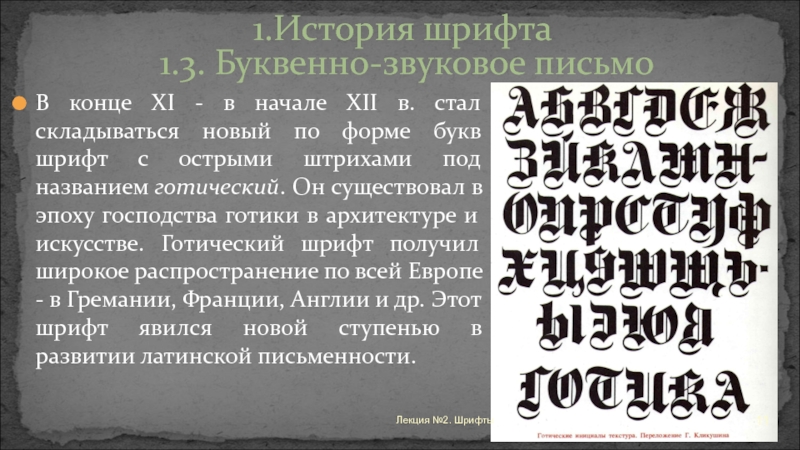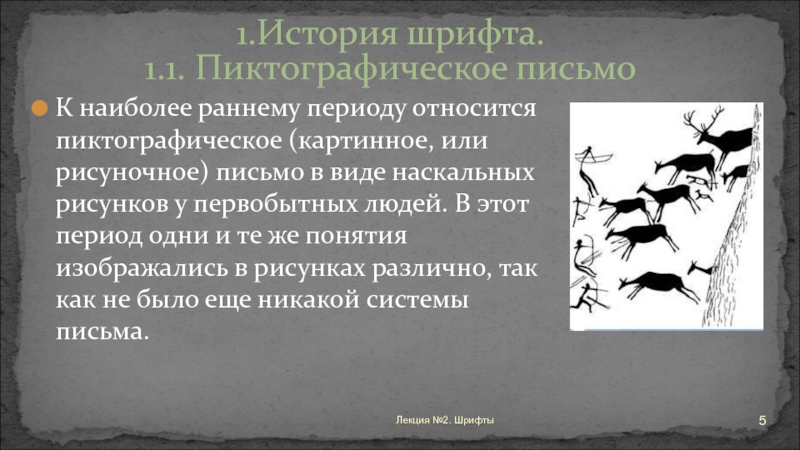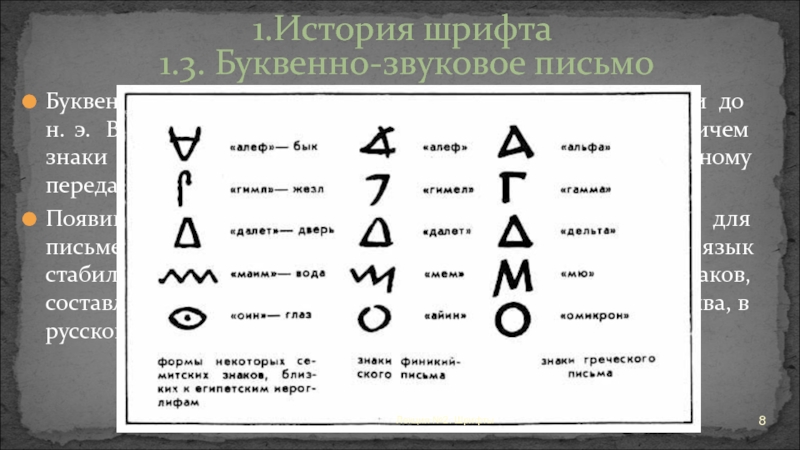
ОФОРМЛЕНИЕ. ШРИФТЫ
Слово "шрифт" в переводе с немецкого означает - начертание букв, письмо. Шрифт - это алфавит с четким определением закономерности построения изображений букв, цифр и других письменных знаков, объединенный в единый стиль.1.
Слайд 1Одно из величайших и важных достижений человечества - это общение
при помощи письменных знаков: шрифта.
ОФОРМЛЕНИЕ. ШРИФТЫ
Одно из величайших и важных достижений человечества - это общение при помощи письменных знаков: шрифта.ОФОРМЛЕНИЕ. ШРИФТЫ
Слайд 2Слово "шрифт" в переводе с немецкого означает - начертание букв,
письмо.
Шрифт - это алфавит с четким определением закономерности построения
изображений букв, цифр и других письменных знаков, объединенный в единый стиль.
1. История шрифта
Слово
Слайд 3Как правило, шрифт разрабатывается с учетом предполагаемой области его использования
- это книжная или журнальная продукция, научная или художественная литература,
детские или учебные издания.
Иногда шрифты, разрабатываются для узкого внутрифирменного применения, становятся всеобщим культурным достоянием. Например, шрифт Times в свое время был разработан для текстового набора газеты "The Times", шрифт Frutiger разрабатывался для визуальных коммуникаций парижского аэропорта
1. История шрифта
Как правило, шрифт разрабатывается с учетом предполагаемой области его использования - это книжная или журнальная продукция, научная
Слайд 4Рисунок знаков прошел длительный и сложный путь, прежде чем он
стал алфавитом. Всего четыре вида письма удалось разгадать:
пиктографическое
идеографическое
слоговое
буквенно-звуковое
1.История шрифта
Рисунок знаков прошел длительный и сложный путь, прежде чем он стал алфавитом. Всего четыре вида письма удалось
Слайд 5К наиболее раннему периоду относится пиктографическое (картинное, или рисуночное) письмо
в виде наскальных рисунков у первобытных людей. В этот период
одни и те же понятия изображались в рисунках различно, так как не было еще никакой системы письма.
1.История шрифта. 1.1. Пиктографическое письмо
К наиболее раннему периоду относится пиктографическое (картинное, или рисуночное) письмо в виде наскальных рисунков у первобытных людей.
Слайд 6В Китае и в Египте на смену пиктографическому письму пришло
идеографическое,  т. е.  письмо при помощи идеограмм, а не букв.
Одним письменным знаком обозначалось целое слово.
Это уже была система графических форм, поскольку последовательность знаков соответствовала порядку слов в речи. Предметы изображались либо символическими знаками (солнце, луна), либо графическими изображениями: птица, зверь и т. д.
1.История шрифта. 1.1. Пиктографическое письмо
В Китае и в Египте на смену пиктографическому письму пришло идеографическое,  т. е.  письмо при помощи идеограмм,
Слайд 7Позднее появилось слоговое письмо, в котором знаками обозначались слоги. Слоговым
письмом древние египтяне писали на папирусе.
Слоговое письмо было громоздким, так
как в нем смешивались словесные и слоговые знаки (клинопись и египетские иероглифы). Виды этого письма существовали много веков у народов Древнего Востока и в странах Восточной Азии –Японии, Китае, Корее.
1.История шрифта 1.2. Слоговое письмо
Позднее появилось слоговое письмо, в котором знаками обозначались слоги. Слоговым письмом древние египтяне писали на папирусе.Слоговое письмо
Слайд 8Буквенно-звуковое письмо появилось во втором тысячелетии  до  н. э.  В
нем знаки означали отдельные звуки (фонемы). Причем знаки в зависимости
от произношения могли по-разному передавать звуковые особенности языка.
Появившаяся буквенно-звуковая система стала основой для письменности многих народов мира. Каждый язык стабилизировался на определенном количестве знаков, составляющих алфавит. (в современном итальянском - 21, буква, в русском -33, в чешском -39, в армянском -39)
1.История шрифта 1.3. Буквенно-звуковое письмо
Лекция №2. Шрифты
Буквенно-звуковое письмо появилось во втором тысячелетии  до  н. э.  В нем знаки означали отдельные звуки (фонемы). Причем
Слайд 9Самый древний почерк латинского письма носит название "капитальное письмо" (I-V
вв.) или "капитальный шрифт".
Капитальное письмо было двух видов: квадратное (красивое,
монументальное) и рустичное ("деревенское").
1.История шрифта 1.3. Буквенно-звуковое письмо
Самый древний почерк латинского письма носит название
Слайд 10Для более быстрого написания текста появился шрифт "курсив" (в переводе
с латинского "наклонный").
Для переписки литературных текстов к IV в. сформировался
так называемый унциал, имеющий буквы искривлённой формы и просуществовал до IX в.
1.История шрифта 1.3. Буквенно-звуковое письмо